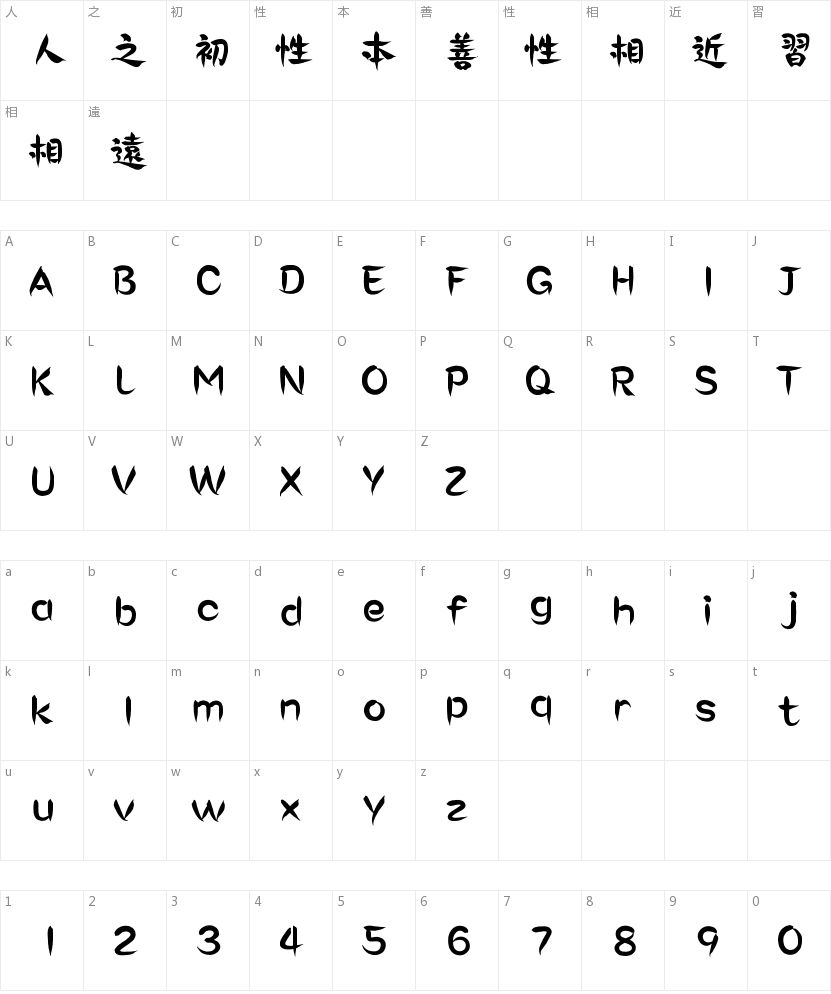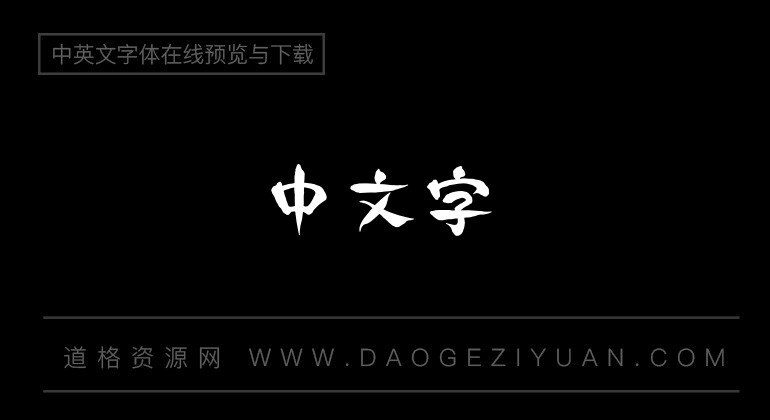
蒙纳繁岚山隶书是一种中国书法字体,它起源于清代,是清代官方字体之一。它是以蒙古族的书写方式为基础,结合中国传统书法而形成的一种独特的书法字体。它以笔画粗细和曲直结合,笔势活跃,结构紧凑,有着浓郁的蒙古特色,是一种极具视觉冲击力的书法字体。文件名:MengNaFanShanLiShu-1.otf
蒙纳繁岚山隶书是一款非常不错的手写艺术字体,具有很好的视觉感,适合于文化类的宣传设计、商业类品牌的广告和产品包装设计以及个性化文字排版等较多场景。